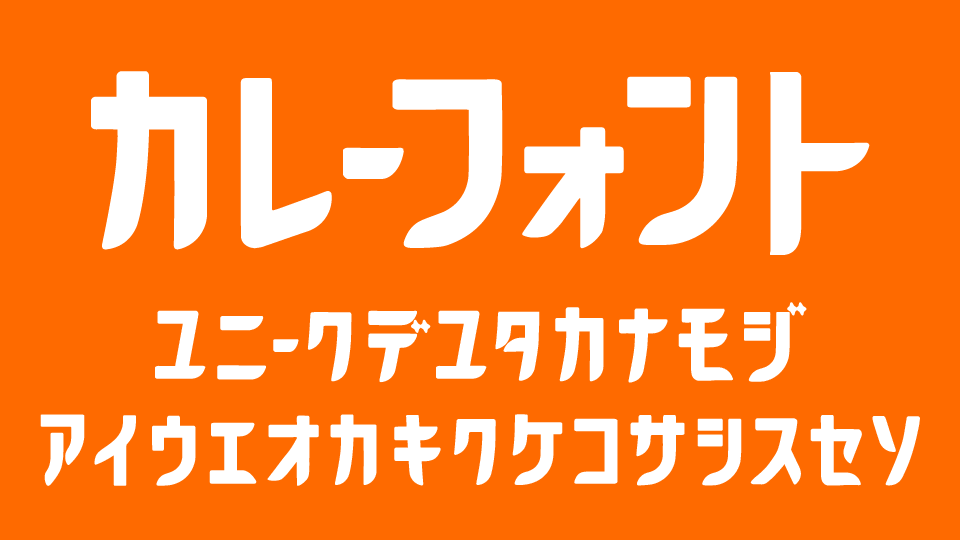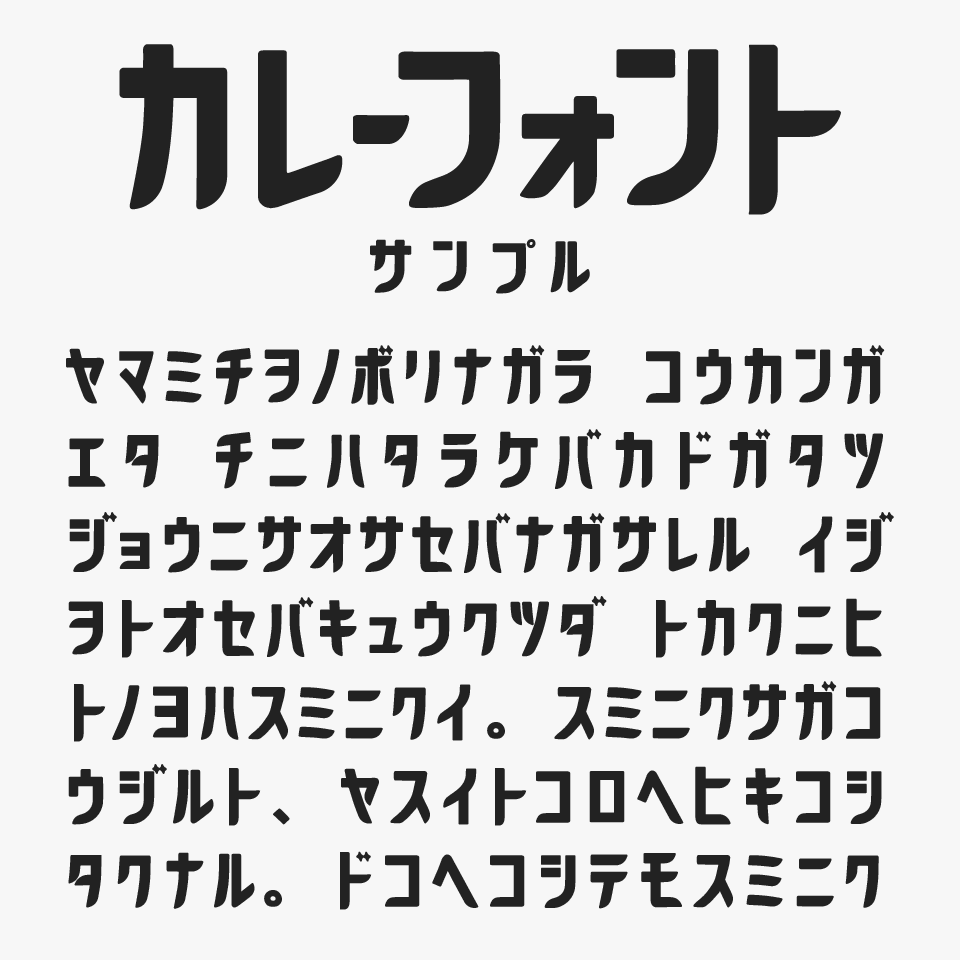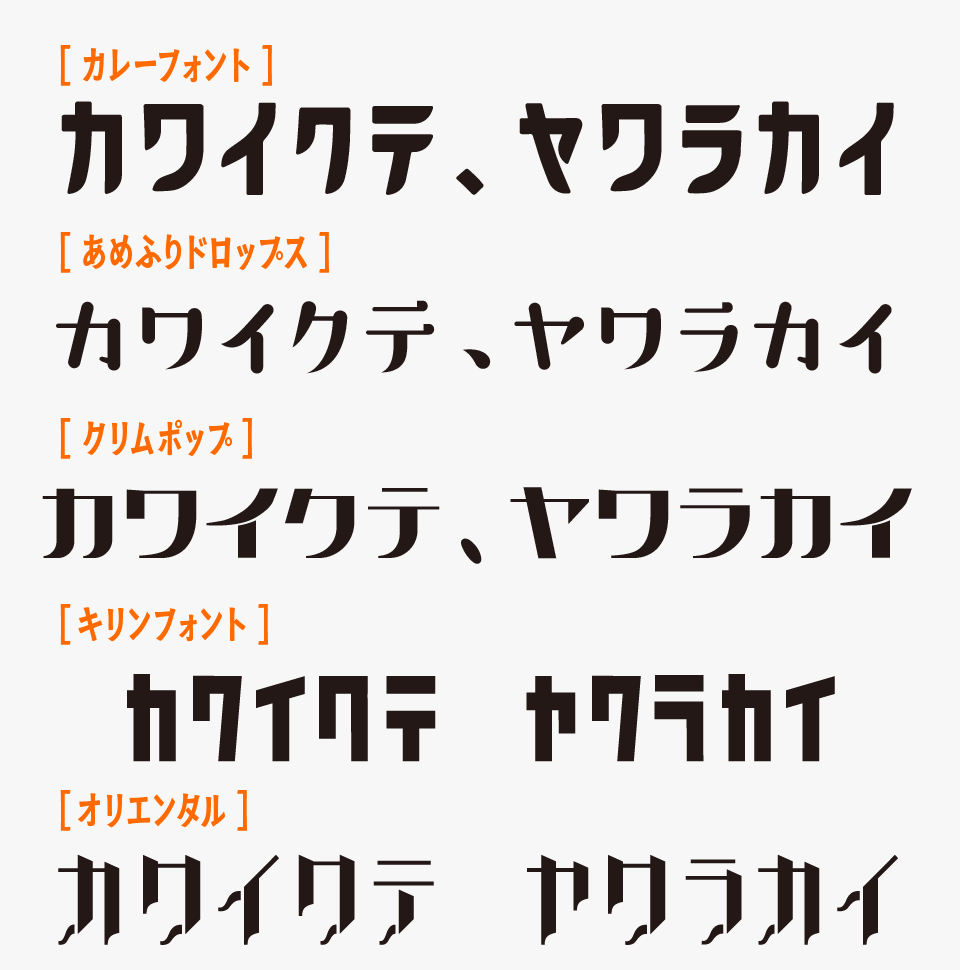
カレーフォント
カレーフォントは、角を丸く整えた太めのゴシック体をベースにした、親しみやすくオリエンタルな雰囲気のあるカタカナフォントです。
ほどよくレトロな雰囲気と素朴な可愛らしさがあり、シンプルながらも印象に残るデザインに仕上がっています。レトロなお店や喫茶店のロゴやメニューなどに合いそうですね。
飲食店のメニューやパッケージ、ポップ、イベント告知など、楽しく親近感のあるデザインにぴったりなフォントです。名前のとおりカレーやグルメ系との相性はもちろん、レトロポップな雰囲気を演出したい場面でもぴったりです。
カレーフォントを、縦長で丸みが特徴的なカタカナフォントと比較してみると、全体的に厚みのあるふっくらとしたシルエットが特徴です。スパイスが溶け込んだようなやわらかなフォルムと、どこか手描き感のある親しみやすい雰囲気フォントです。
比較フォントは、「あめふりドロップス」「クリムポップ」「キリンフォント」「オリエンタル」と使用していますが、どれも特徴的なカタカナが可愛いフォントなので、ぜひあわせてチェックしてみてください。
収録文字は、カタカナ・アルファベット・数字・記号が収録されています。